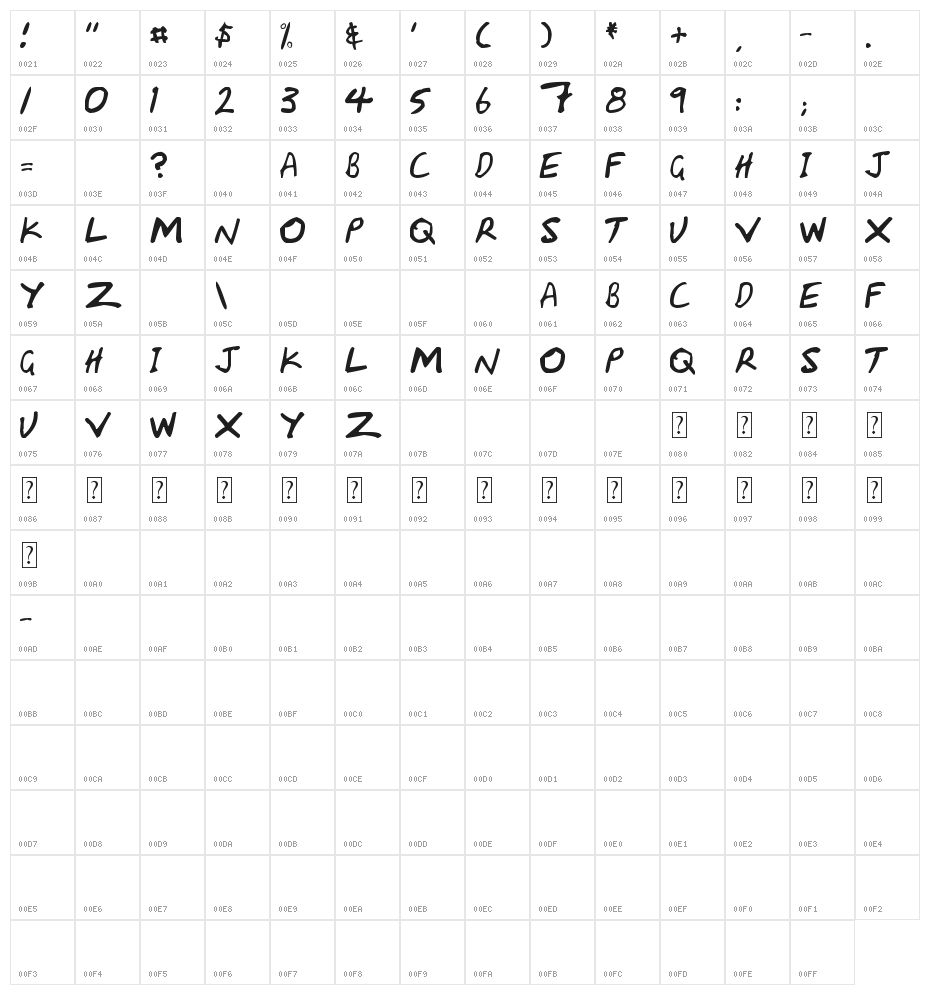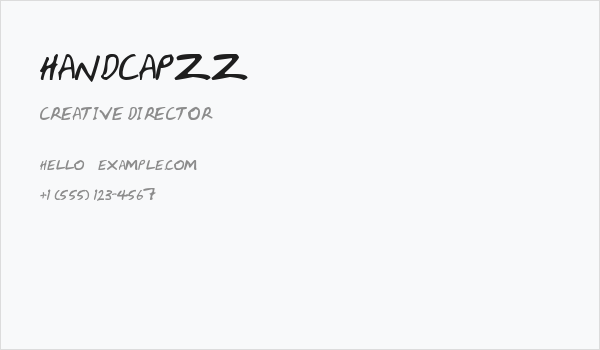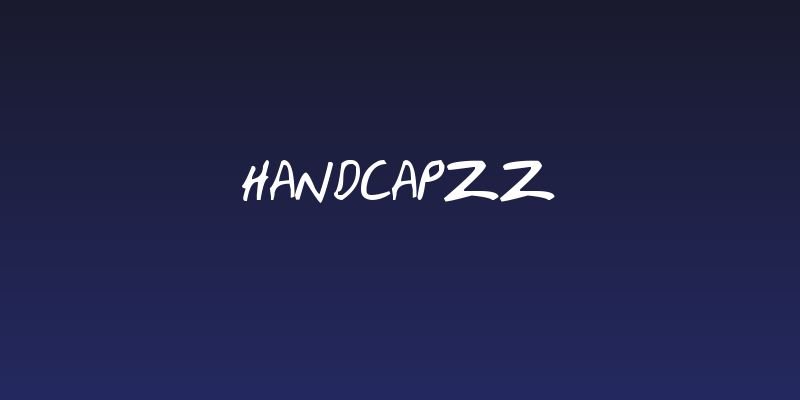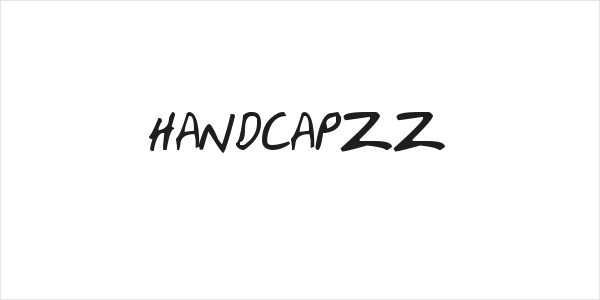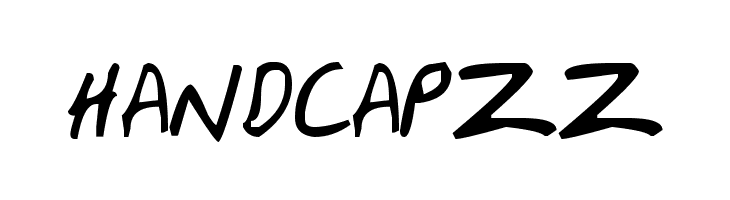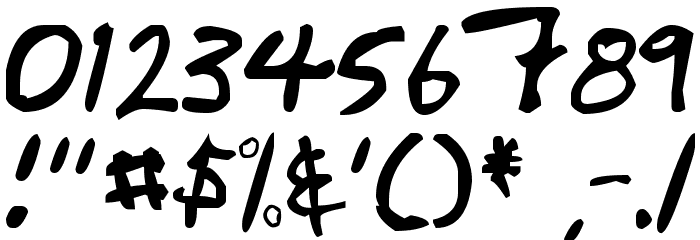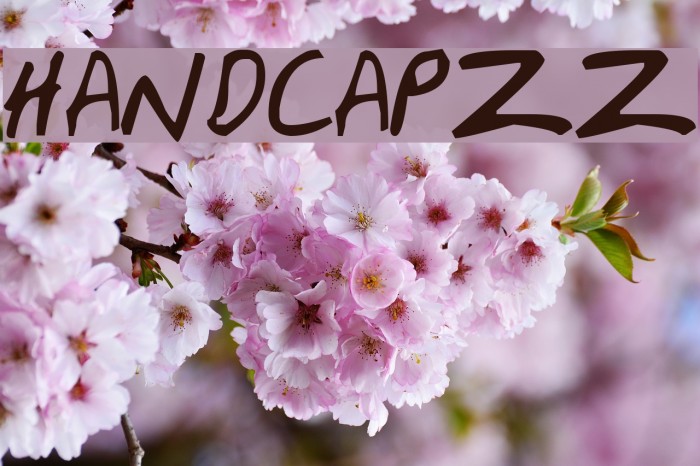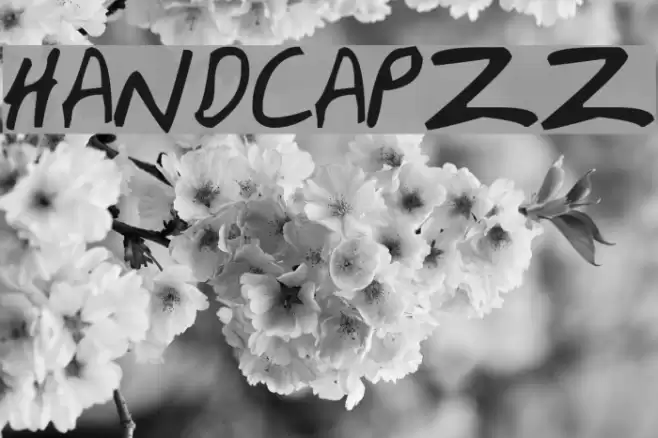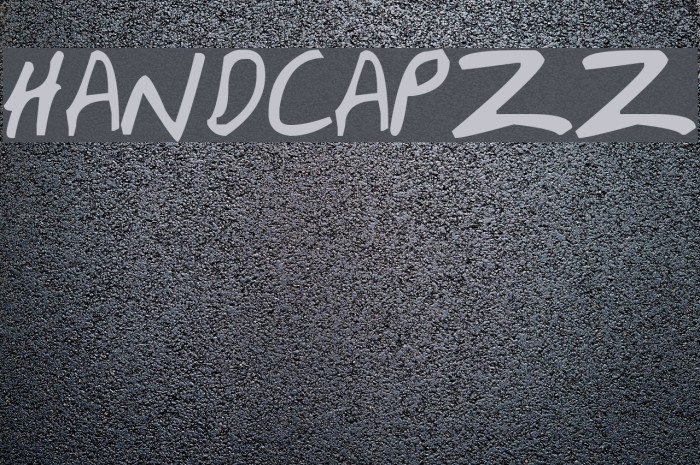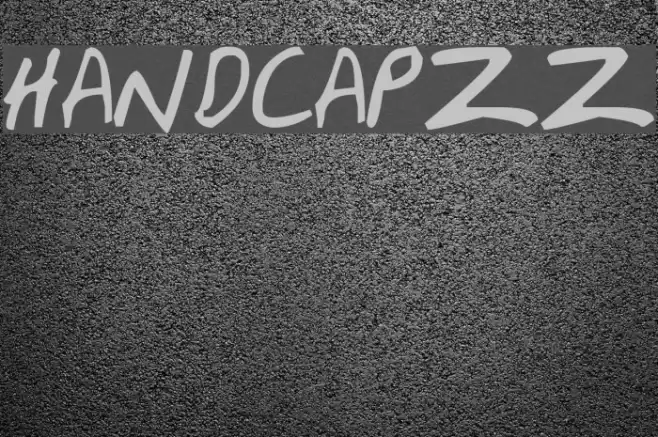
HandCapzz Font
| Общий стиль | Casual and Playful |
| Область применения | Headlines, Logos, Informal Text |
| Рекомендуемые проекты | Ideal for greeting cards, invitations, posters, and branding materials that aim to convey a personal and lively message. |